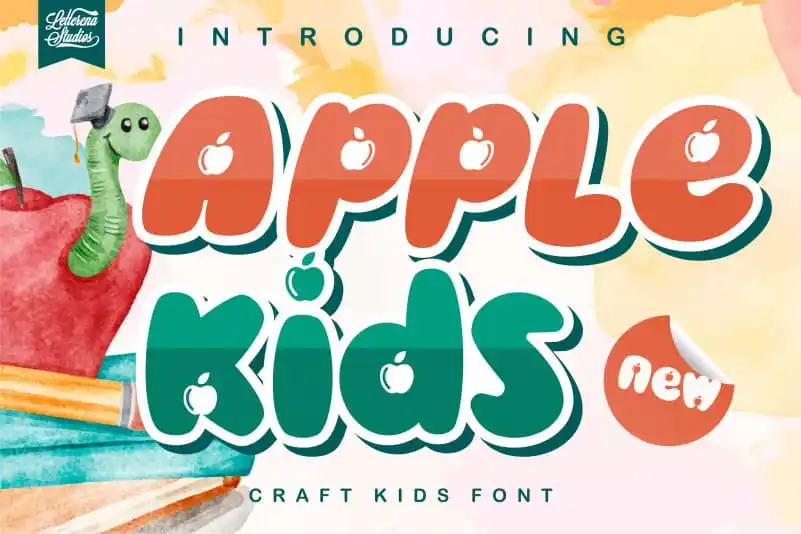
Apple kids – Crafting Kids Font – Fonte Grátis
Apple kids - Crafting Kids Font
A fonte ‘Apple Kids – Crafting Kids Font’ é uma opção única para designers que desejam dar aos seus projetos um toque fresco e moderno. Com este design display, os elementos são criados de formas simples e divertidas, ideal para aplicar em logomarcas, gráficos para crianças ou até mesmo como letras do menu de seu próximo restaurante infantil. Aqui está uma fonte perfeita para atingir o público infantil com um toque de criatividade. O estilo vibrante e a personalização dos traços garantem que seja fácil ler em qualquer tamanho, tornando-a uma escolha ideal tanto para projetos comerciais quanto para iniciantes no design gráfico. A designer letterenastudios soube capturar o espírito jovial da infância com esta criação única. Para utilizar a fonte ‘Apple Kids – Crafting Kids Font’, o cliente deve pessoalmente comprar e usar por seu próprio benefício (ou seja, não comercial). É uma excelente maneira para adicionar um toque divertido aos seus projetos de design gráfico.